| 【清和堂のご紹介】 清和堂は、タイプフェイスデザイナー多田信之氏が手掛けるファウンダリーです。フラッグシップ書体である清和堂明朝体は文字の流れをとても大切にしています。作品と読者の間に現れる特別な空気感を常にイメージして製作しました。本文用書体の奥深さを追求「読みやすさ」「心地よさ」を大切にした本文用書体をゼロから考察、清和堂明朝体シリーズを開発致しました。 |
清和堂明朝体について
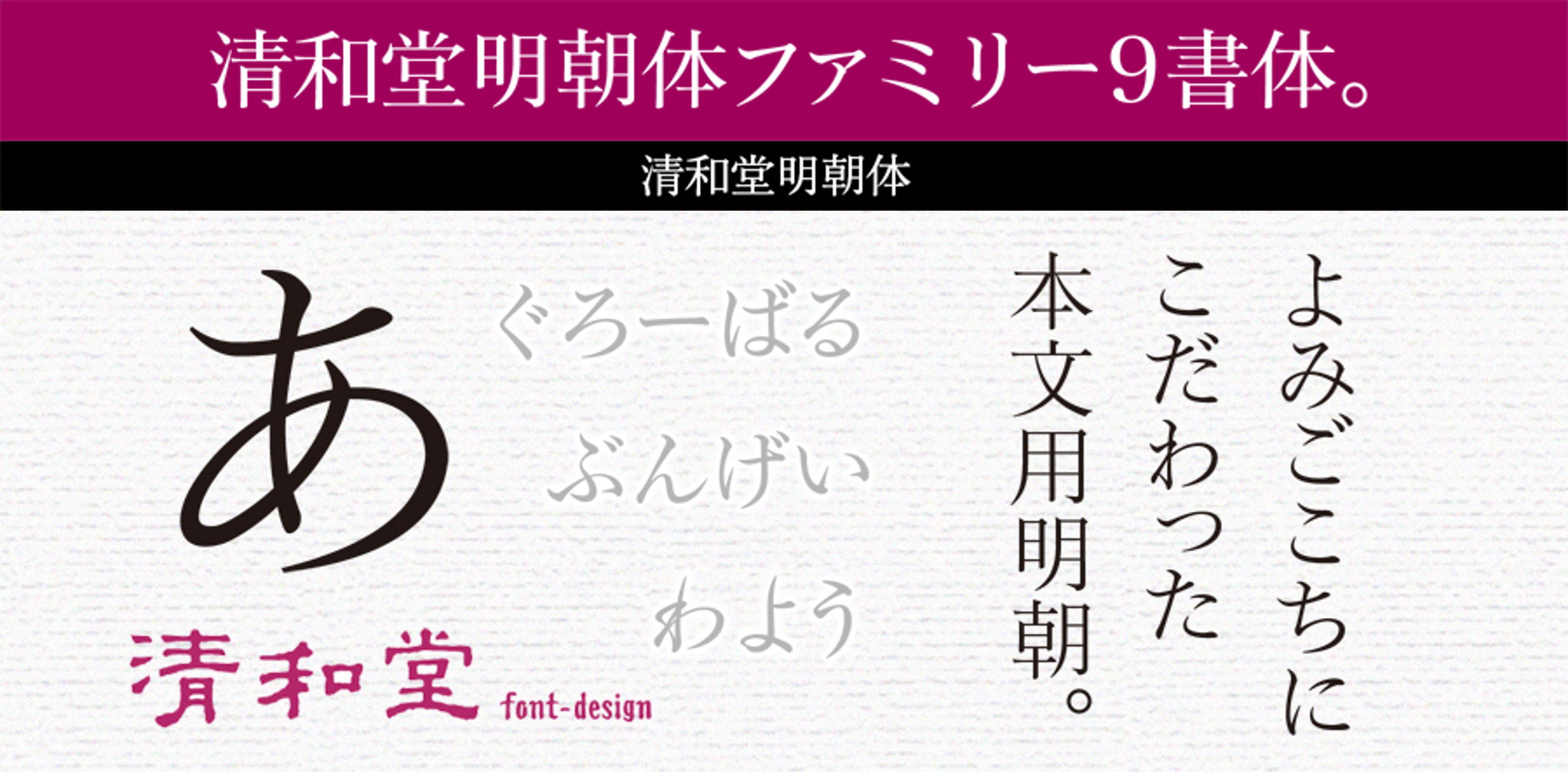
清和堂明朝体は、写植メーカーの時代から本文用の明朝体を見詰めてきた作者が、写植時代の美しいフォルムを進化させ、また今までの本文明朝体になかったほど良い懐の締め具合に調整してデザインした新たな本文用明朝体。汎用性の高い漢字に合わせて様々な仮名のシリーズを展開します。
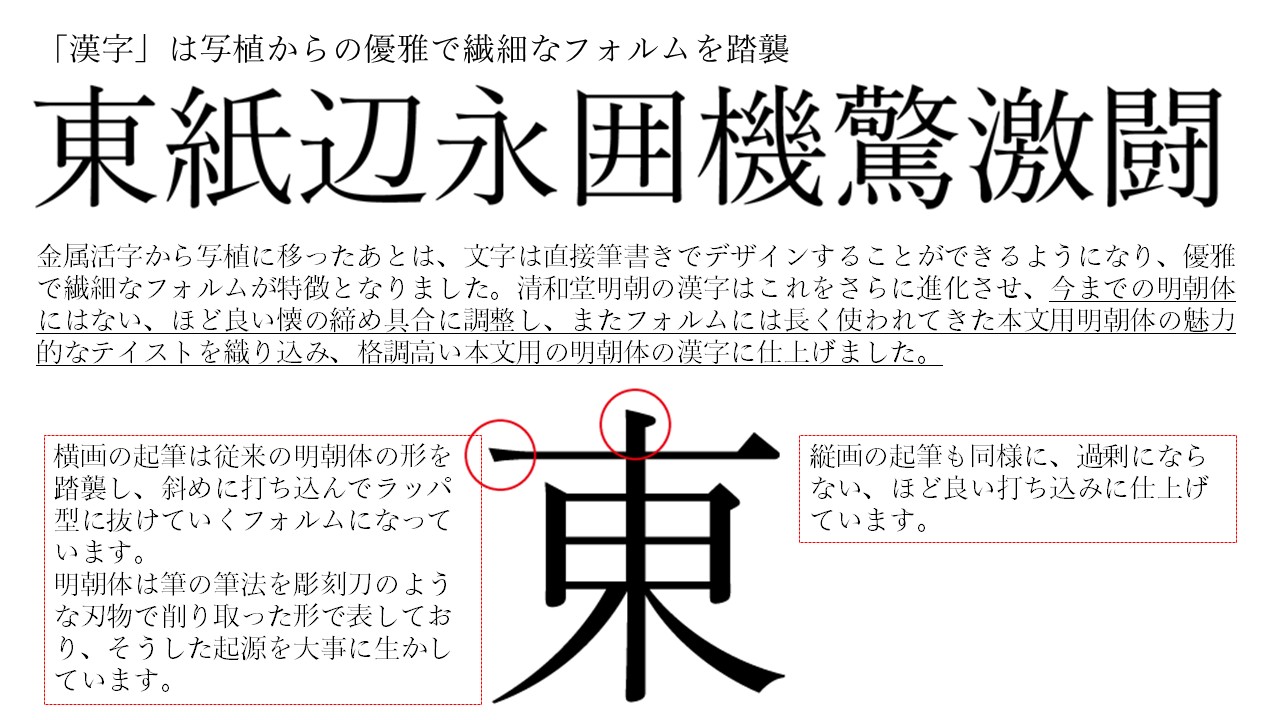
「清和堂明朝体 global」について「清和堂明朝体 global」は、グローバル仮名。フラッグシップ書体として、それぞれの文字固有の形を大事にしながら、標準性・汎用性、無駄がない鍛えあげたボディ、Bauhausによる「形体は機能に従う」という基本思想を追いかけ続け、使い勝手をよくするために読む事に特化した理想的なフォルムを追求しました。一見オーソドックスに見える骨格に、文章の流れを止めない、不必要で無駄な視線の動きを排除する工夫が施されています。3ウェイトをご用意しています。(L / R / M) |
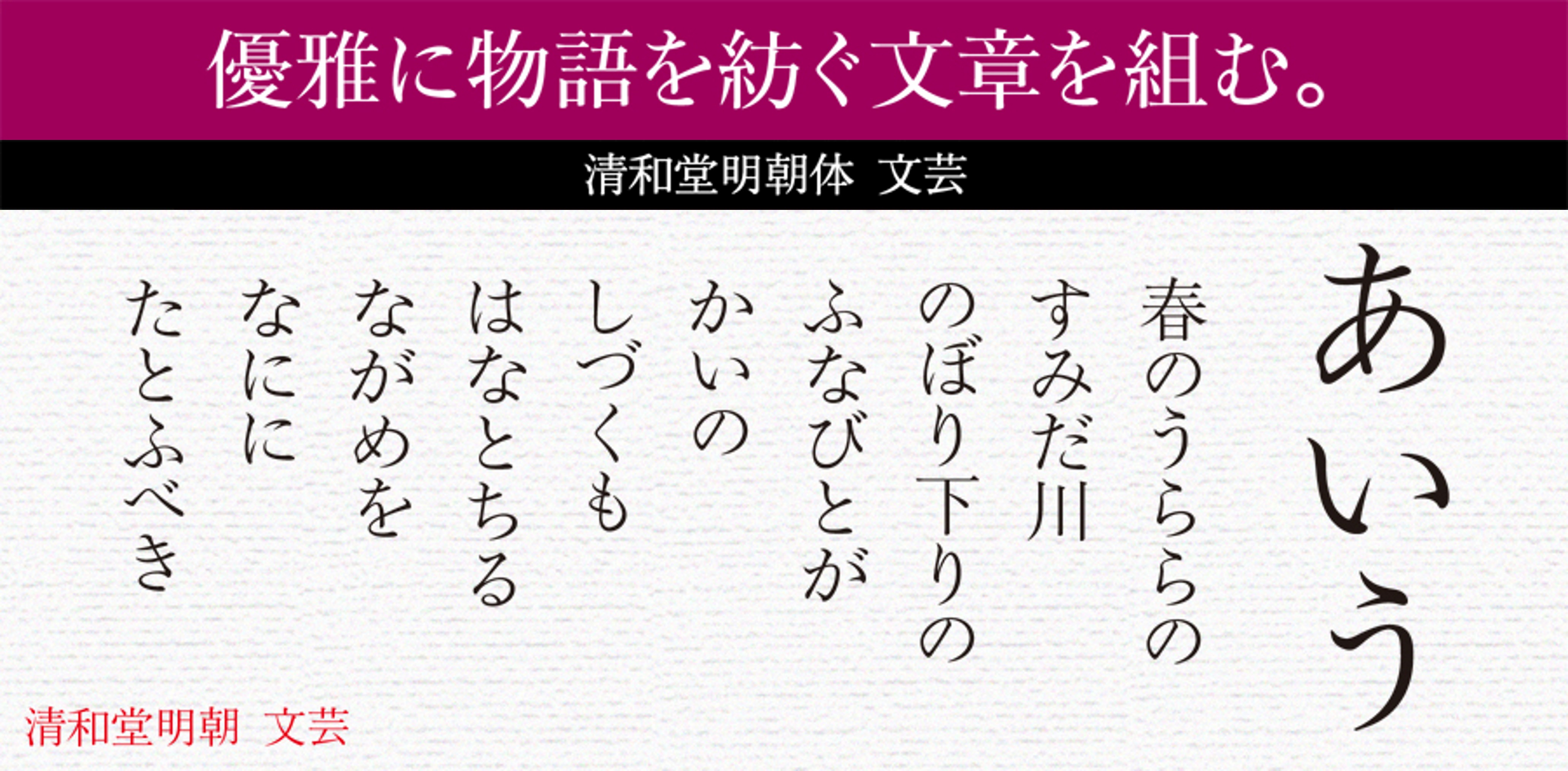
「清和堂明朝 文芸」について「清和堂明朝 文芸」は、文庫で使われてきた写植の書体をもっともっとと時間をかけて贅沢に熟成させました。筆書きのストロークを取り入れ、より肉筆に近いイメージで設計されております。骨格の曲線が筆書きに近いため、手描きのリズムの心地よさが出るように筆脈の流れを調整しています。3ウェイトをご用意しています。(L / R / M) |
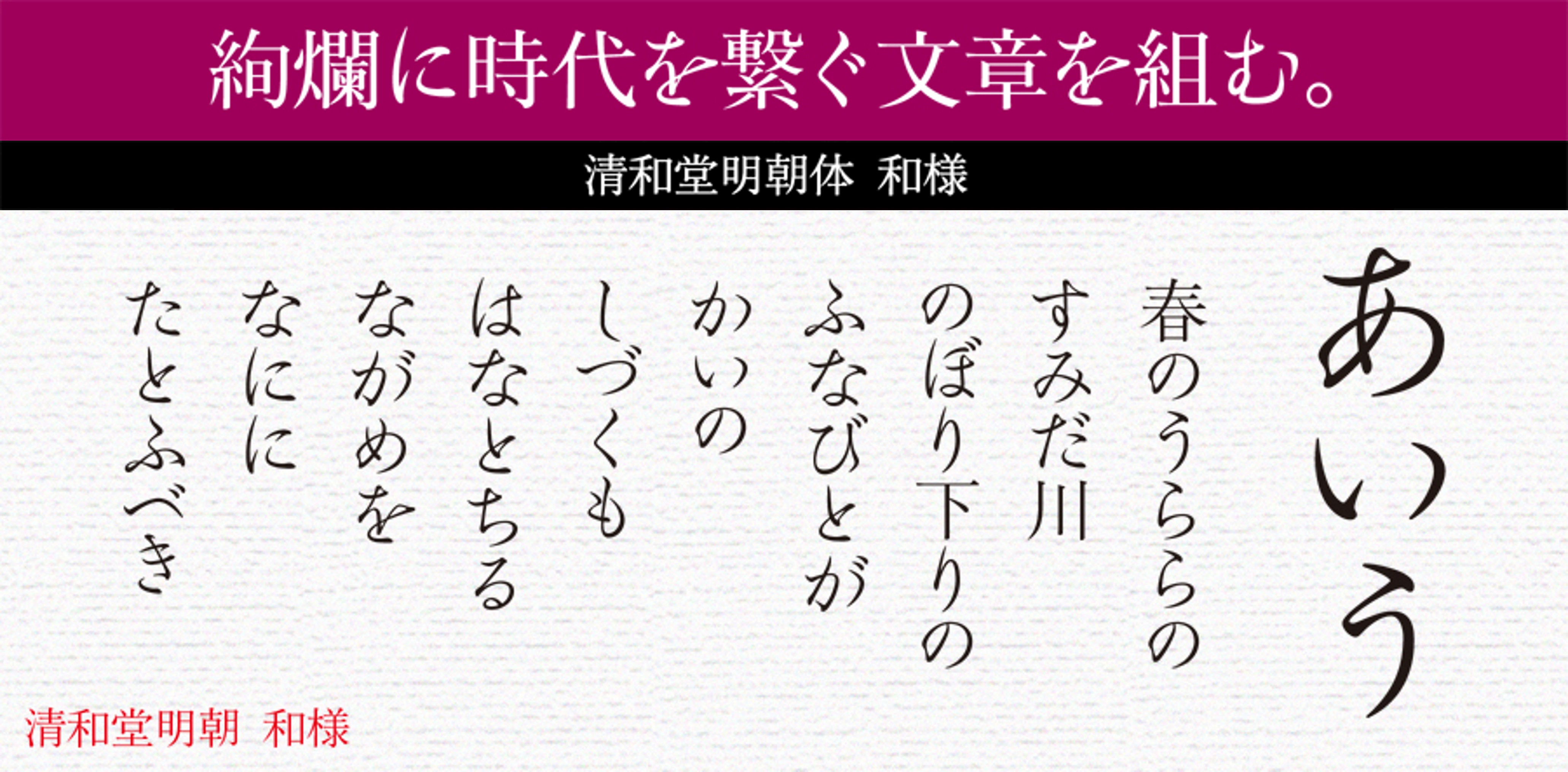
「清和堂明朝 和様」について「清和堂明朝 和様」は、今までなかった、明朝体と組み合わせた行書仮名、和様仮名。金属活字は一切意識していません。江戸時代の偉大なグラフィックデザイナー尾形光琳に憧れて燕子花のフォルムを目一杯叩き込んでみました。和の洗練されたたおやかさを表現しています。3ウェイトをご用意しています。(L / R / M) |
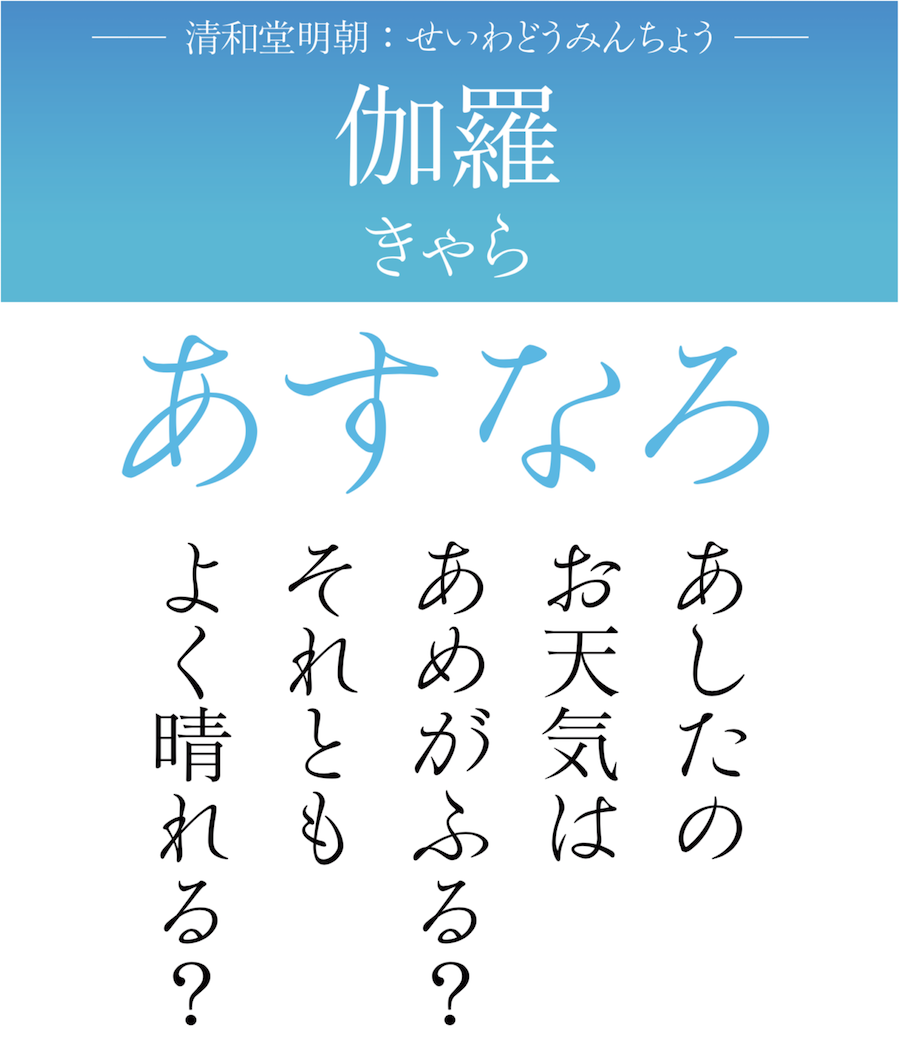
「清和堂明朝 伽羅(きゃら)」について「清和堂明朝 伽羅(きゃら)」は、高級香木「伽羅」の薫り高い優雅なイメージを表現。仮名は、プロポーションに加え、ペアカーニングを搭載しました。OpenType機能で、固有の文字幅と適切な字間で組むことができます。伽羅の仮名は今までの明朝体とは一味違った、とっても個性的なエレメントです。 |
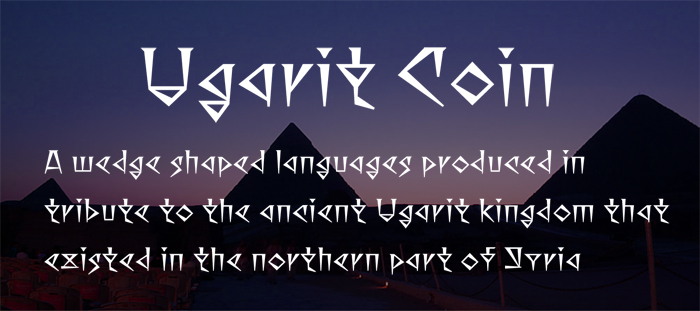
楔形欧文「Ugarit Coin(ウガリト コワン)」について楔形欧文「Ugarit Coin(ウガリト コワン)」は、現在のシリア北部にあった古代都市ウガリト。この遺跡から発見された紀元前14世紀から13世紀頃の文字板にある最後期の楔形文字がウガリト語です。シュメール文明最後期ウガリト王国の遺跡から発掘されたアルファベットを示す楔形文字。清和堂フォントはこのウガリト王国へのオマージュ作品として楔形のフォルムで欧文を制作し、書体名は、1929年フランスの探検隊が発掘したことからフランス語で「楔」を意味する「coin」(コワン)を冠して「Ugarit Coin(ウガリト コワン)」と命名しました。 |